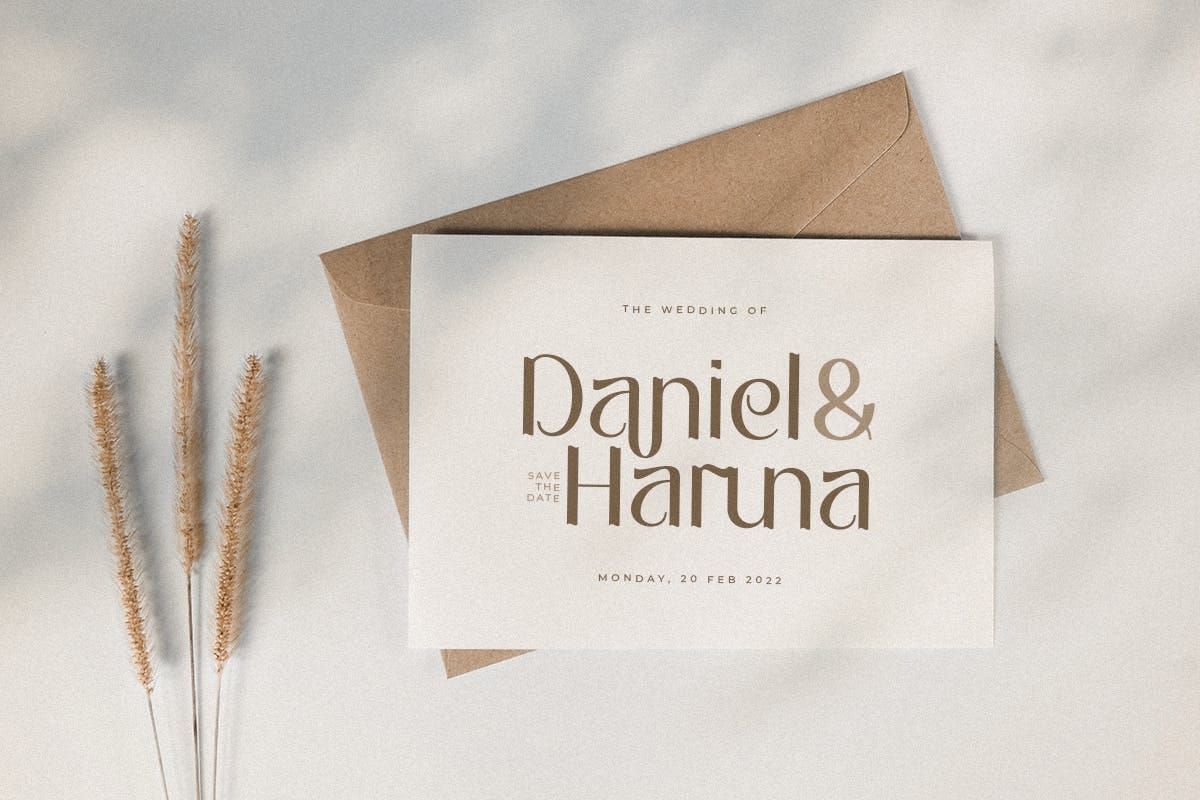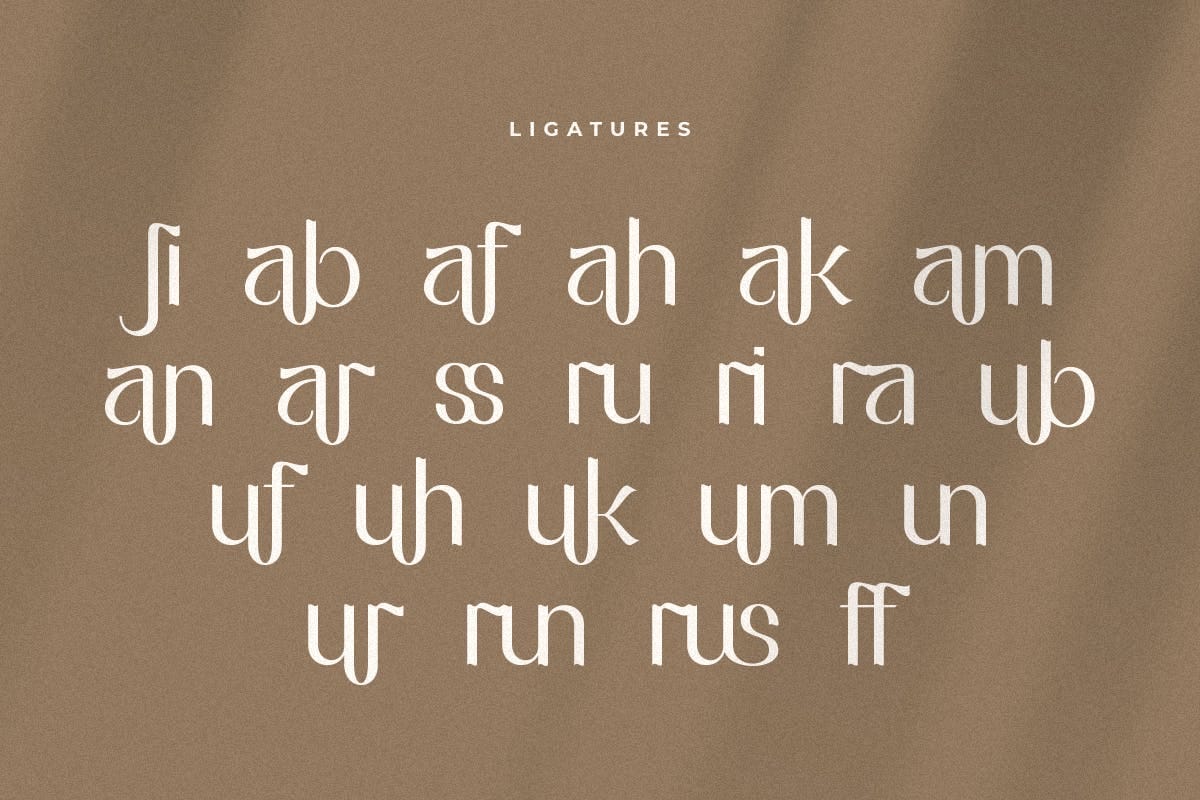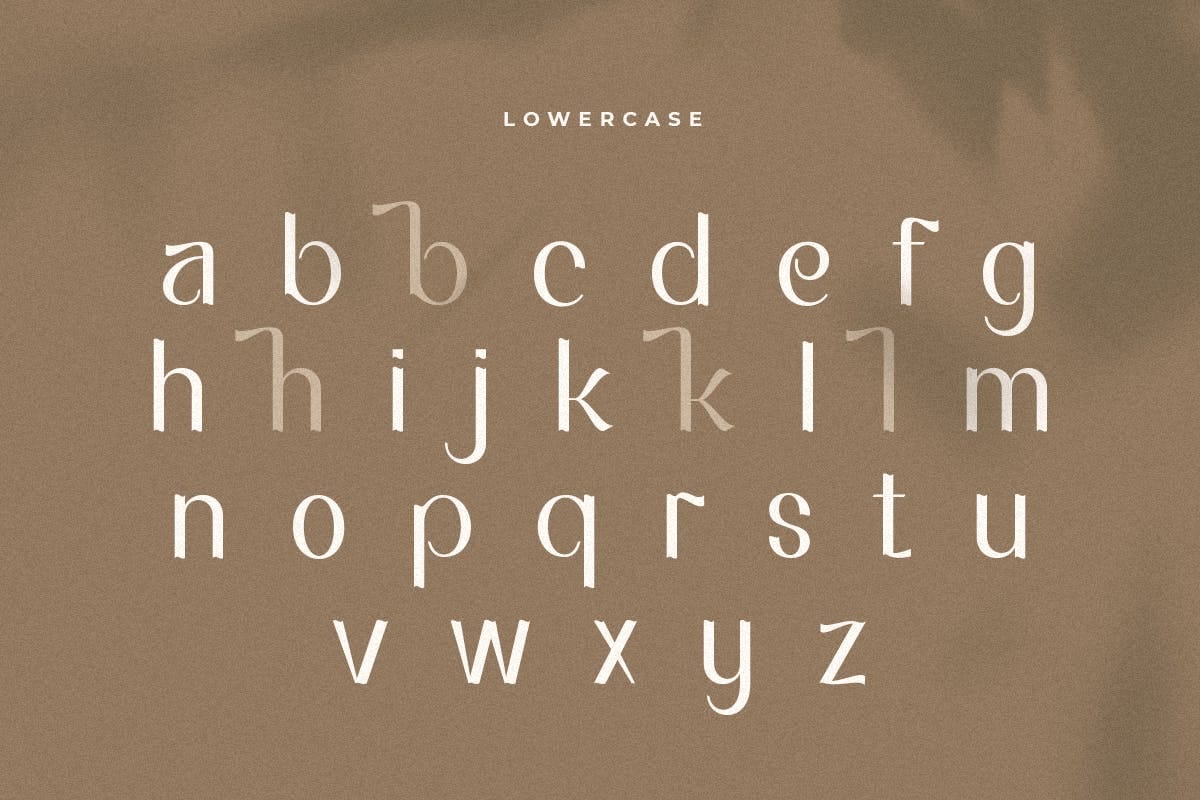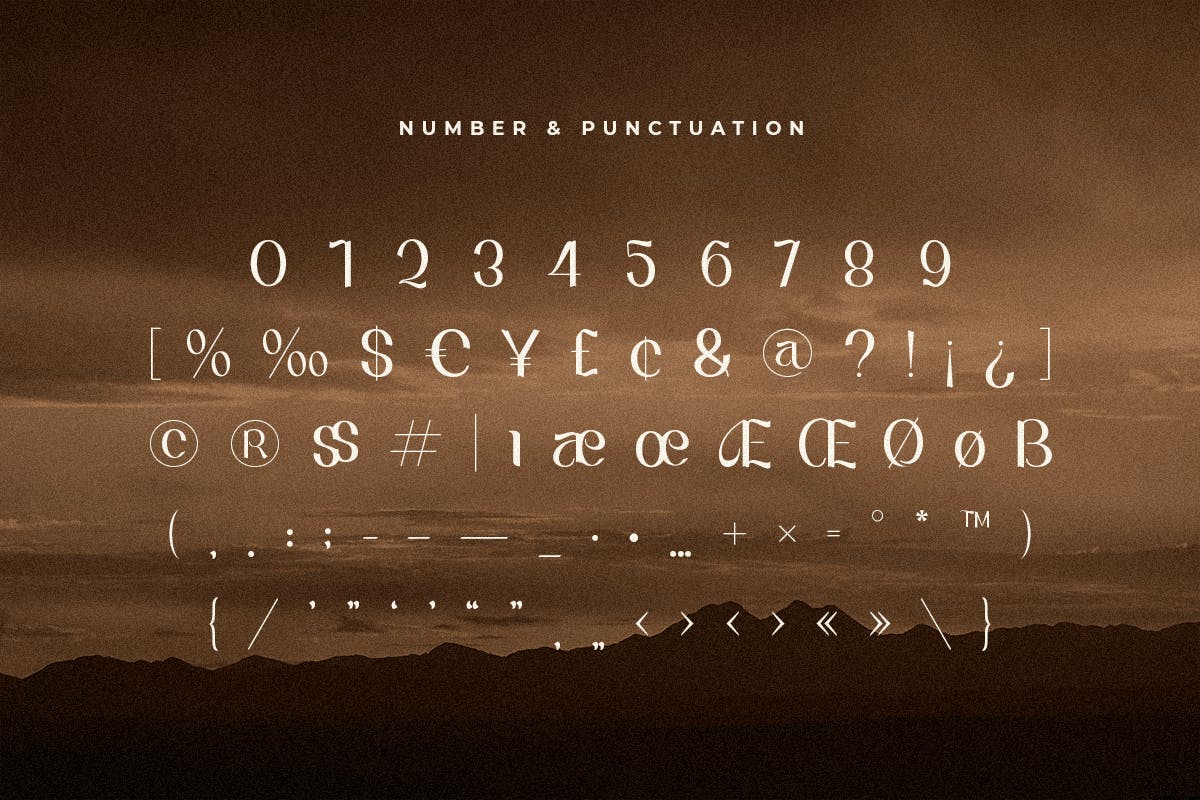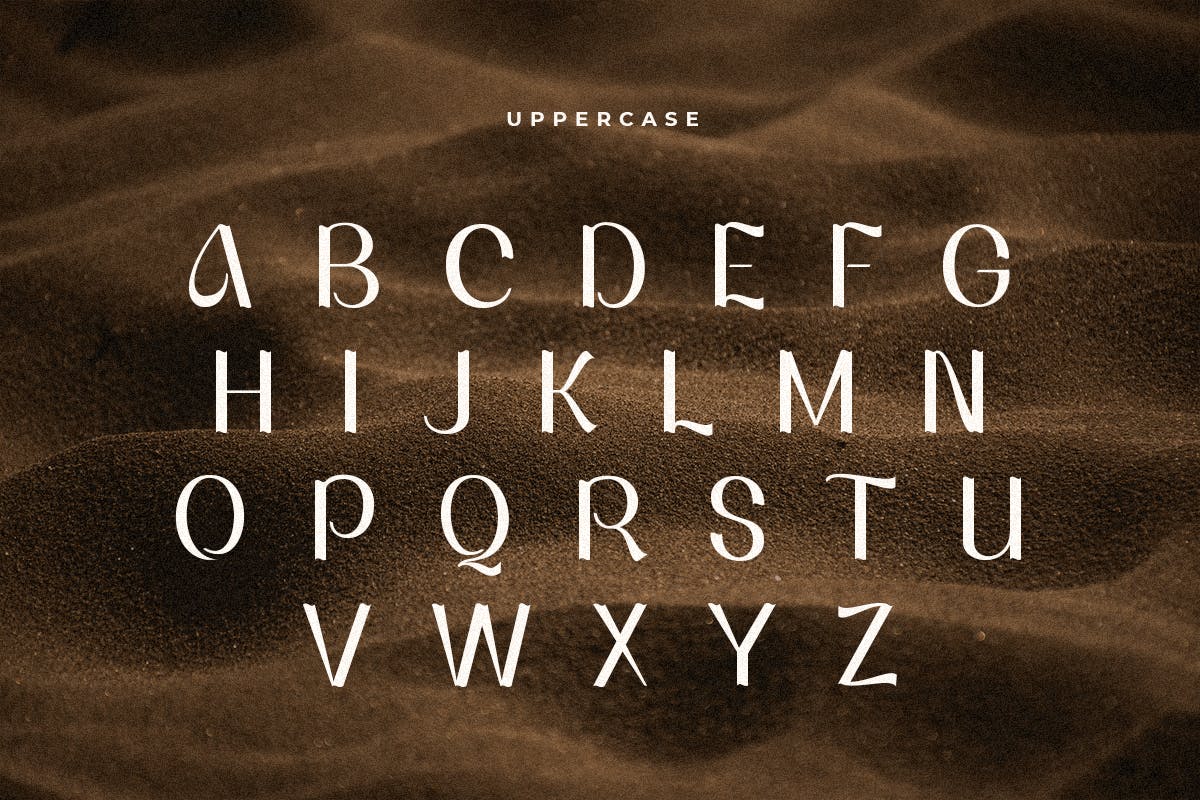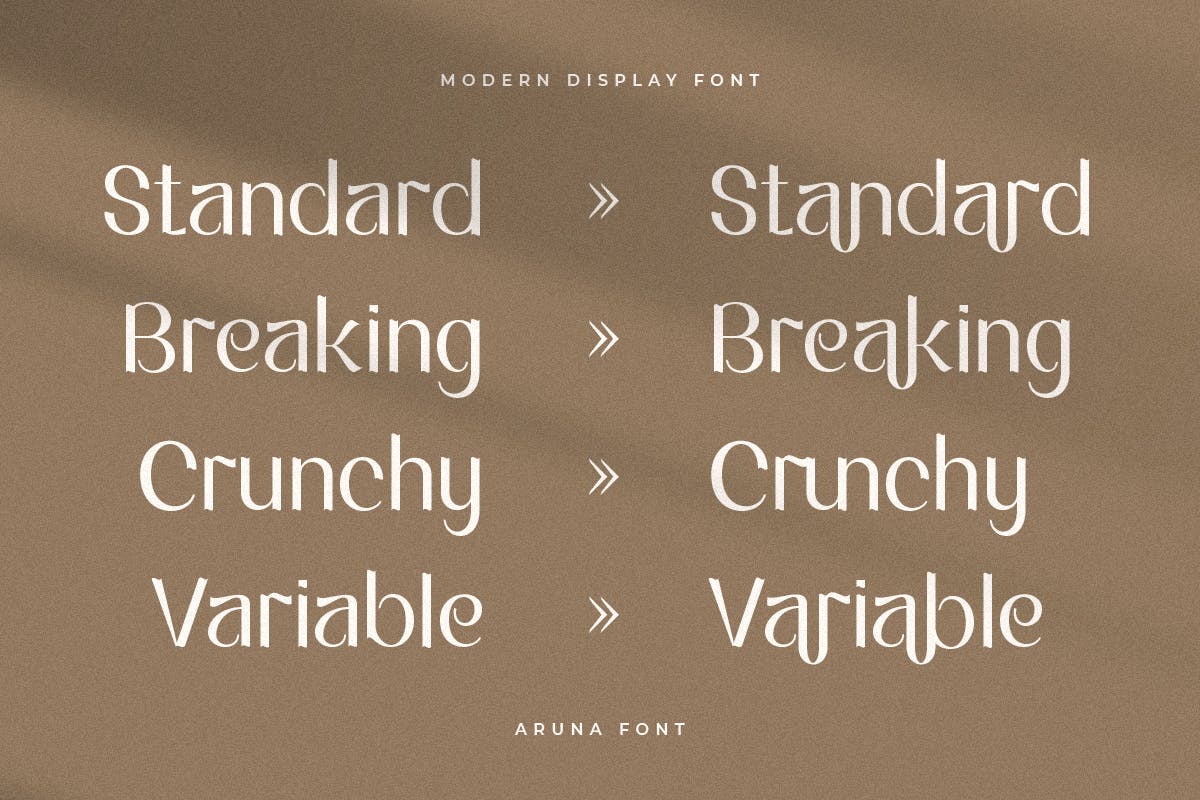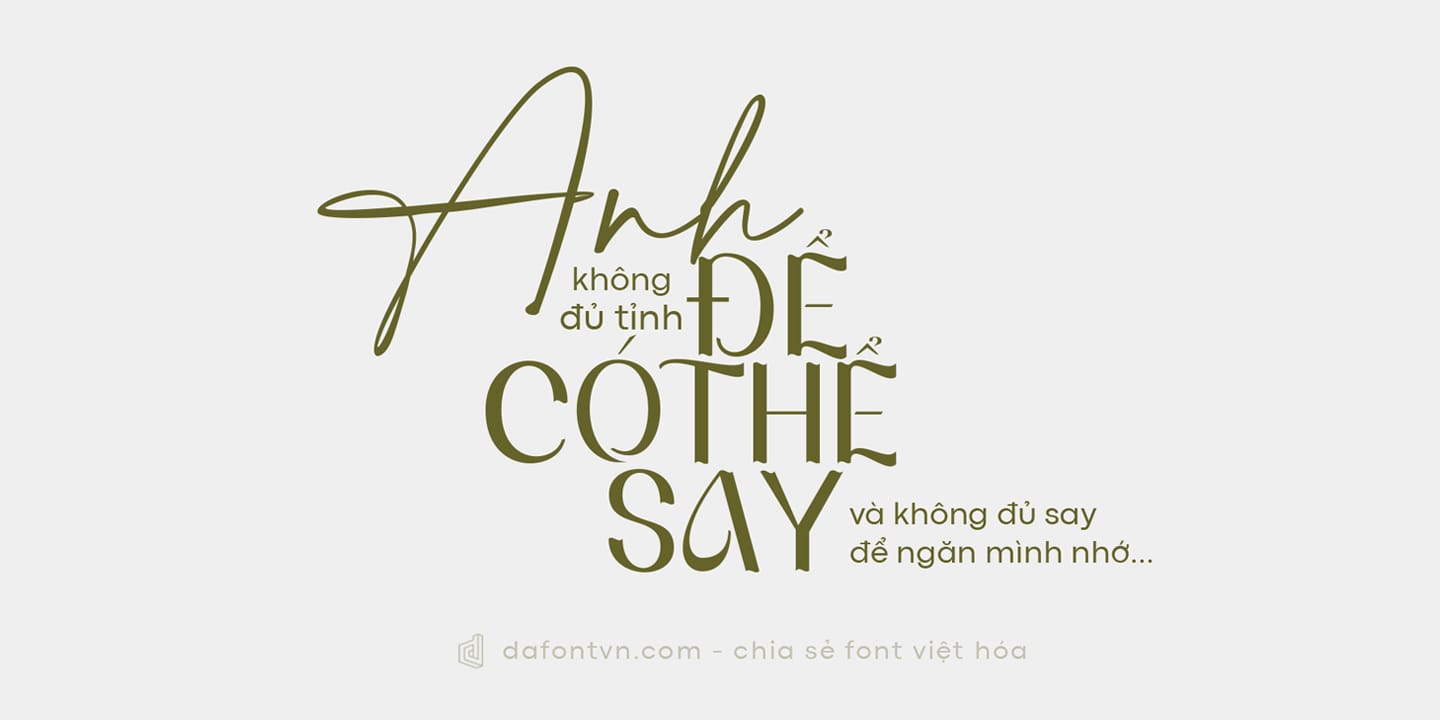
Font Aruna Việt Hóa là một phông chữ display hiện đại, được tạo ra đặc biệt cho các thiết kế như xây dựng thương hiệu, có thêm chữ ghép phong cách độc đáo để bạn có thể áp dụng cho các thiết kế khác nhau. Aruna Modern Display bao gồm các ký tự thường và chữ in hoa, đi kèm với ligature, font được việt hóa đầy đủ và chỉnh sửa lại để phù hợp với các dấu tiếng Việt.